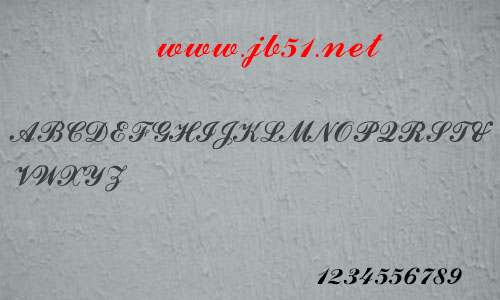
Ford script卷曲英文字體,字體筆觸粗細(xì)適中,字形優(yōu)美,具有很好的視覺(jué)感,僅支持英文字母,適合應(yīng)用于藝術(shù)設(shè)計(jì)、平面宣傳設(shè)計(jì)、網(wǎng)頁(yè)設(shè)計(jì),書(shū)法字帖等領(lǐng)域,需要的朋友快來(lái)本站下載使用吧!